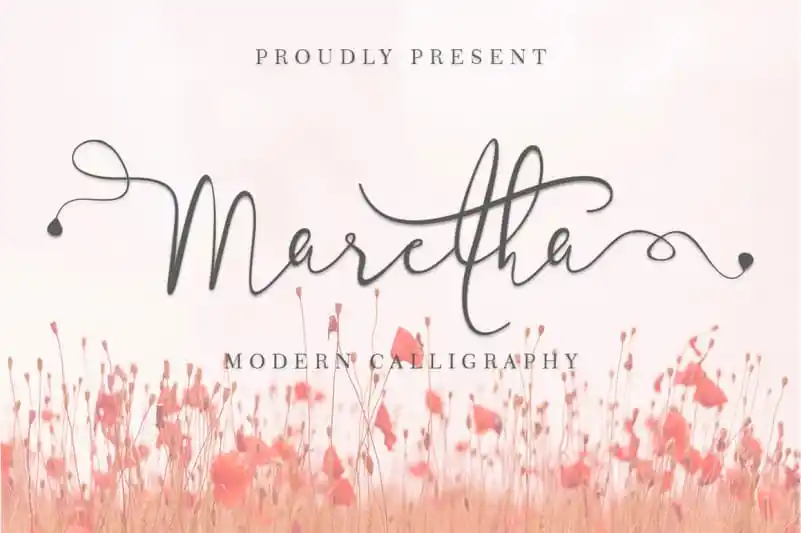
Maretha Calligraphy Font – Fonte Grátis
Maretha Calligraphy Font
A fonte Maretha Calligraphy é perfeitamente adequada para quem busca uma aparência elegante e moderna no seu trabalho. Nascida do amor pela letra calligrafizada, essa fonte se destaca especialmente para eventos de casamento, fotografias de casamentos, convites de casamento, identidade visual, e logotipos bonitos. Além disso, ela também é perfeita para escrever frases românticas para casais, citações ou decorar suas viagens. O designer Yoga Letter criou um recurso que complementa sua personalização única, tornando a escrita mais atraente e sofisticada em uma variedade de contextos. Seja para adicionar um toque especial aos seus trabalhos de marca, projetos de identidade visual ou mesmo para aquela frase romântica perfeita no seu diário ou até mesmo para adicionar beleza ao seu próximo álbum de viagens, Maretha Calligraphy certamente encaixa-se em vários cenários.